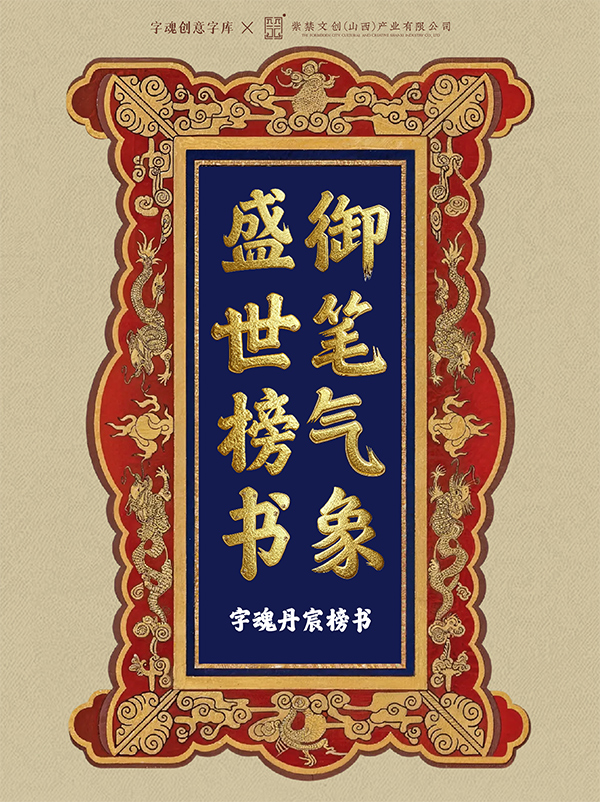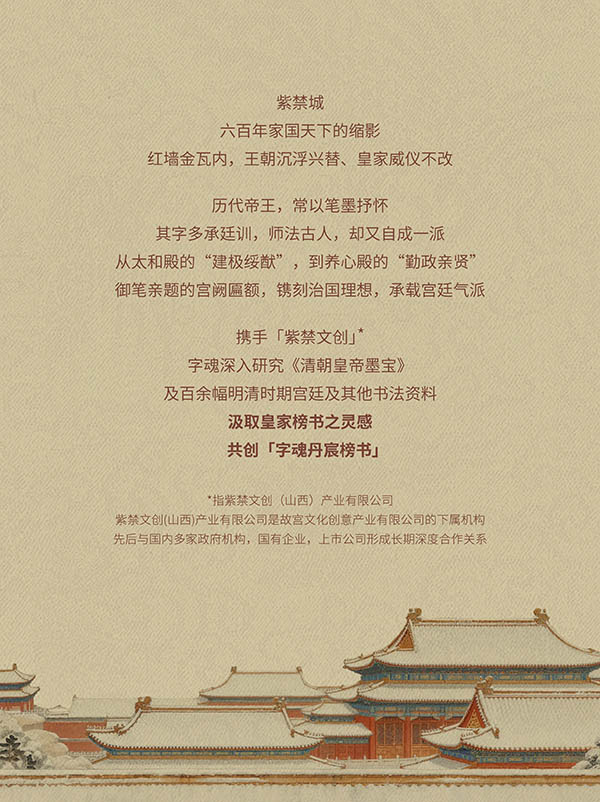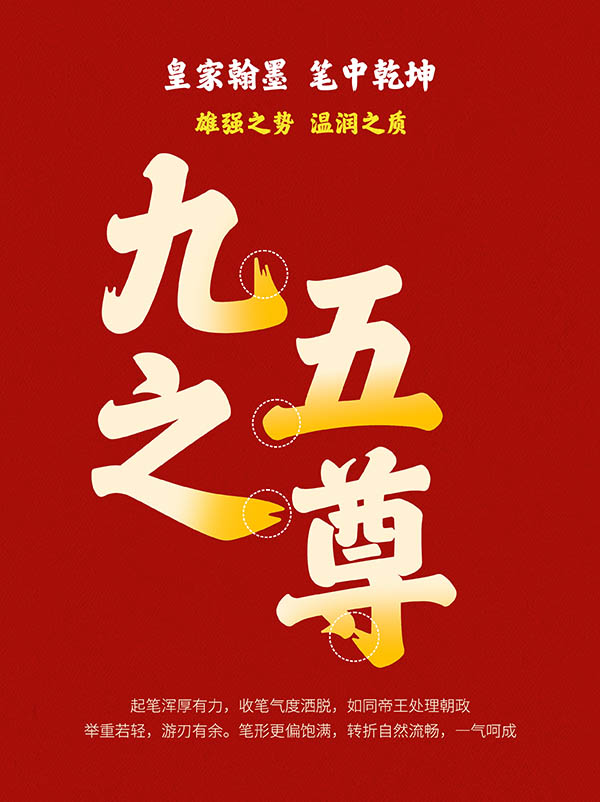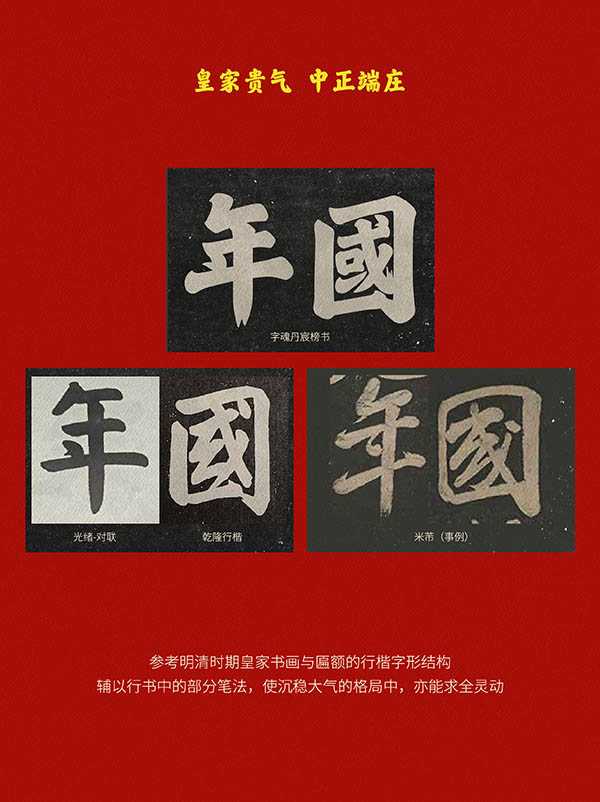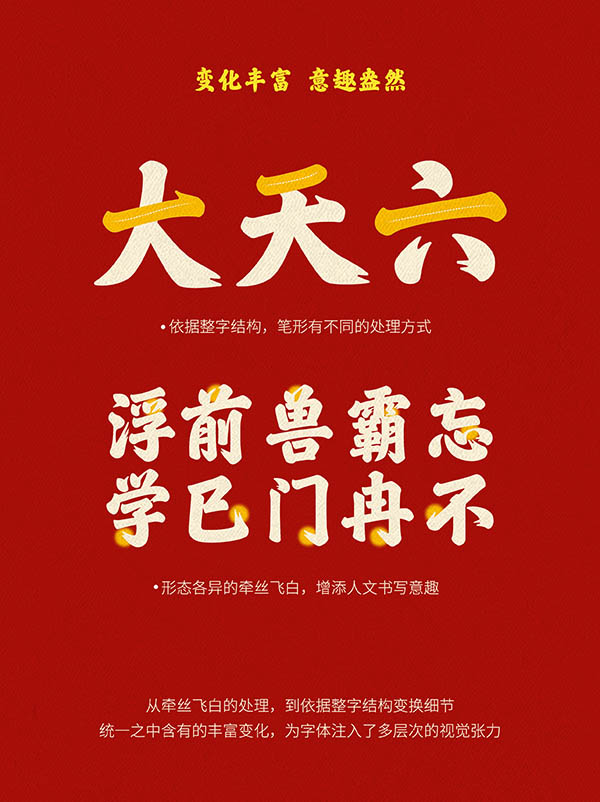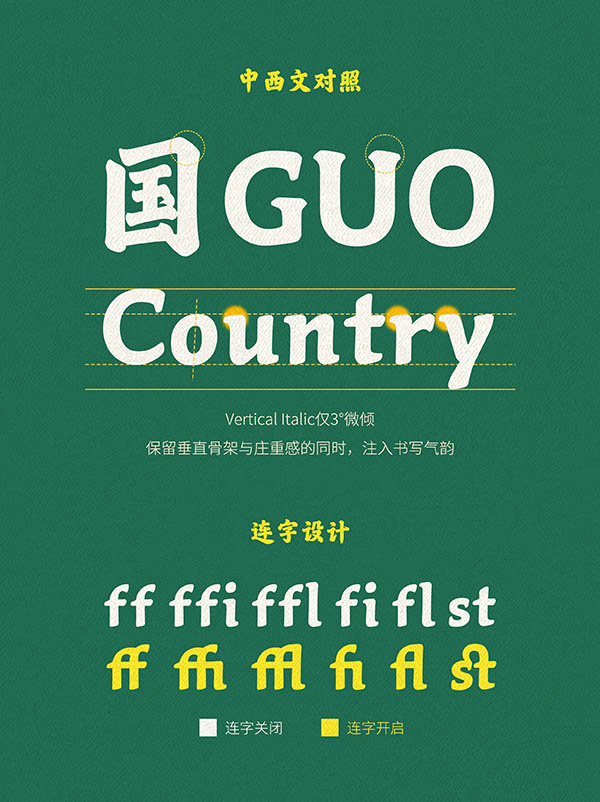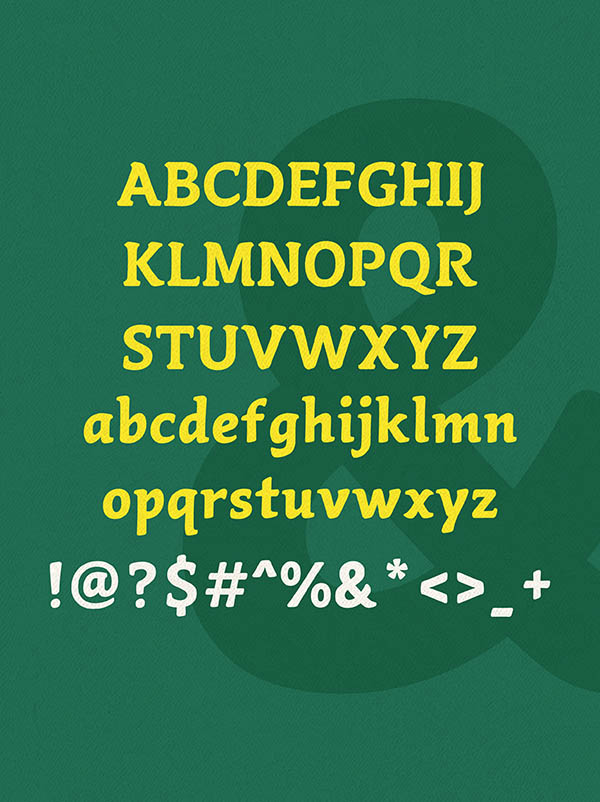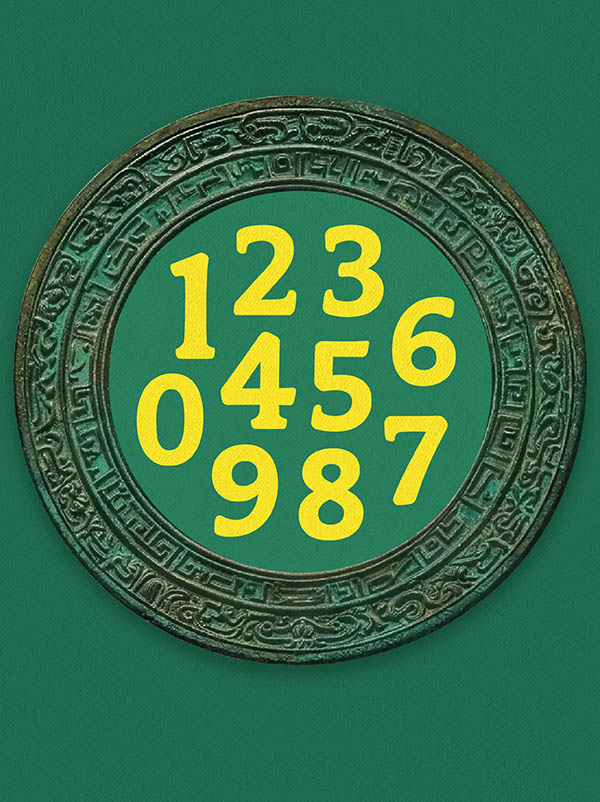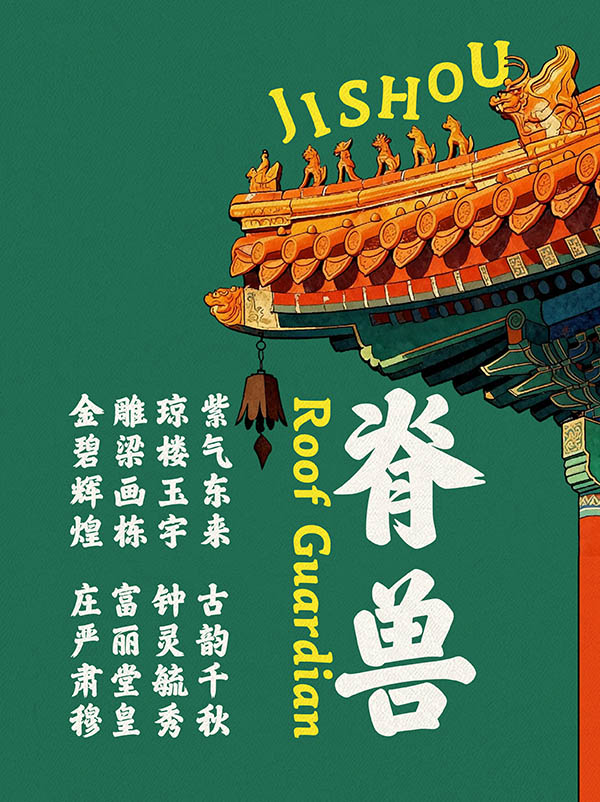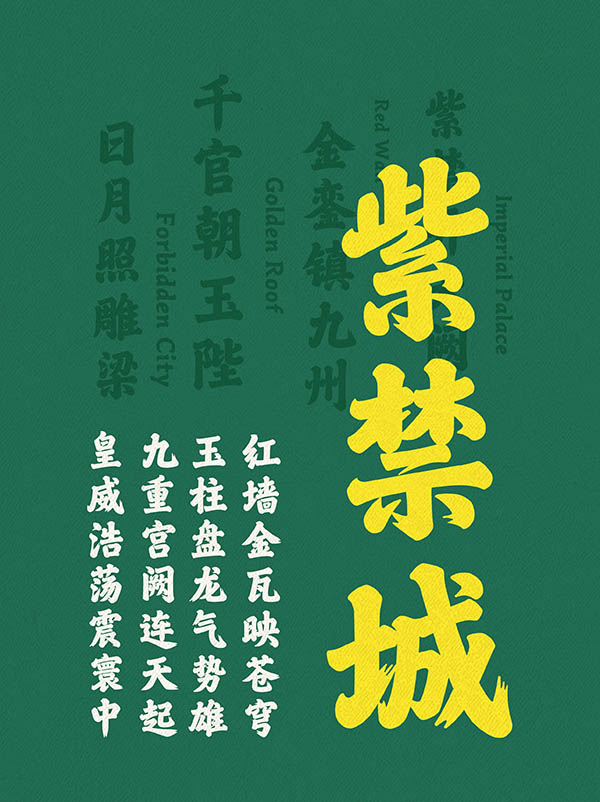
字魂 × 紫禁文创重磅发布「字魂丹宸榜书」,赋能传统文化 IP焕新
数字化浪潮下,文博 IP 竞争已进入文化符号深度构建的新阶段,定制字体正成为品牌资产运营的核心利器。行业数据显示,目前国内已有超 20 家头部博物馆落地专属定制字体。近期,字魂与敦煌画院、吴文化博物馆等机构合作推出的多款定制字体,更是引发了行业广泛关注。这一趋势充分说明,定制字体作为关键视觉载体,正逐步成为文博 IP 从产品售卖向品牌资产运营升级的核心竞争力。
近日,国内字体定制领军品牌字魂再度发力,携手紫禁文创,将明清皇家气象注入数字时代,正式推出重磅定制字体「字魂丹宸榜书」。紫禁城作为中华宫廷文化的集大成者,红墙金瓦间藏着家国气象,殿宇匾额里镌刻着御笔风骨,字魂以皇家榜书为核心灵感,深度萃取明清朝翰墨精髓,将其转译并固化为极具辨识度的 IP 视觉符号,让沉睡的宫廷书法以全新字体形态焕活新生,也让定制字体深度植入文博传播生态,持续为大众带来高质感的文化体验。
文博类IP本身深度承载着历史底蕴,标准化通用字体不仅难以承载深厚的文化底蕴,更无法形成专属且连贯的品牌记忆,尤其对于紫禁文创这类顶级文化 IP 而言,大众化的通用字体难以承载其厚重的宫廷气韵,更无法支撑起传统文化符号的构建与传播。
而一套量身打造的定制字体,能够凝练 IP 独有的美学气质,在展览呈现、文创开发、品牌传播等全场景中,构建统一且具有辨识度的文化体验。
「字魂丹宸榜书」以皇家贵气为内核,呈现中正端庄之姿,设计团队深度参考明清时期皇家书画与宫殿匾额的行楷字形结构,巧妙融入行书笔法,让沉稳大气的整体格局之中更添灵动气韵;同时兼具雄强之势与温润之质,起笔浑厚有力,收笔洒脱大气,笔形饱满圆润,转折自然流畅,整体一气呵成。
在细节处理上更是变化丰富、意趣盎然,从牵丝飞白的细腻营造,到依字形结构灵活调整笔画细节,于统一规范之中蕴藏丰富变化,为字体赋予层次饱满的视觉张力。
此外,字体配套西文以 15 世纪经典书法为创作基底,采用 Vertical Italic 风格灵感与书写姿态,在简化字形的同时强化软笔书法质感,整体兼具文艺复兴时期书法人文体的优雅美感与 Italic 字体的书写韵律,笔画间融入专属装饰风格,不刻意追求与中文字形一一对应,而是实现中西美学意蕴的通融呼应,小写部分则在保留核心设计特点的基础上适当弱化装饰以提升阅读体验,无论作为标题、正文独立使用,还是与中文搭配组合排版,均能呈现出和谐统一、高级雅致的视觉效果。
在数字化浪潮席卷文化产业的当下,定制字体正在重新定义文博IP的表达方式,定制字体不仅是信息传递的载体,更是文化传承与品牌升级的重要桥梁,助力中华优秀传统文化在数字时代焕发新生、广泛传播,未来将成为更多IP解锁传播新路径,实现品牌升级的关键举措。
定制字体的核心价值,在于实现文博 IP 文化基因的数字化转译。不同于通用字体的同质化,定制字体可深度提取文物美学、书法笔触,地域文化符号等元素,将抽象的文化内核转化为可感知和传播的视觉语言,让古老文明以字体作为载体,让现代大众可以在日常视觉接触中感受传统文化魅力,推动文化传承年轻化落地。
对于致力于构建“超级IP”的文博机构而言,视觉体验的统一性至关重要。定制字体如同一根纽带,能为文博 IP 构建统一的视觉护城河,串联线上线下全场景应用,可应用于文博文创,品牌包装,出版传媒,导视系统,展览美陈等全场景。广泛应用的同时可以消除视觉割裂感,强化品牌记忆,让用户快速识别 IP 特色。
在国潮兴起的背景下,文博IP通过定制字体打破了"高冷”的刻板印象,年轻时尚的展示拉近了Z世代消费者。据相关行业数据显示,64.4%的用户关注字体的传统文化内涵。文博类定制字体往往自带“国潮”属性,极易在社交媒体上引发传播。
字体是功能载体,更是文化容器。对于文博类IP而言,一款定制字体已经逐渐成为品牌视觉资产的战略选择。而一款优秀的定制字体更能让中华优秀传统文化焕活新生,打破时间和空间的限制,在现代生活中持续传播和传承。